Khi download Microsoft Office, người dùng sẽ cùng lúc nhận được rất nhiều font chữ có sẵn. Đó là những font đơn giản, dễ nhìn và được mọi người trên khắp thế giới sử dụng.
Các ứng dụng chuyên biệt hơn, chẳng hạn như Microsoft Publisher, có nhiều font chữ lạ mắt được tự động đưa vào. Nếu mọi người muốn có font chữ độc đáo cho những dự án đặc biệt vào trong Microsoft Office thì sau đây là hướng dẫn chi tiết.
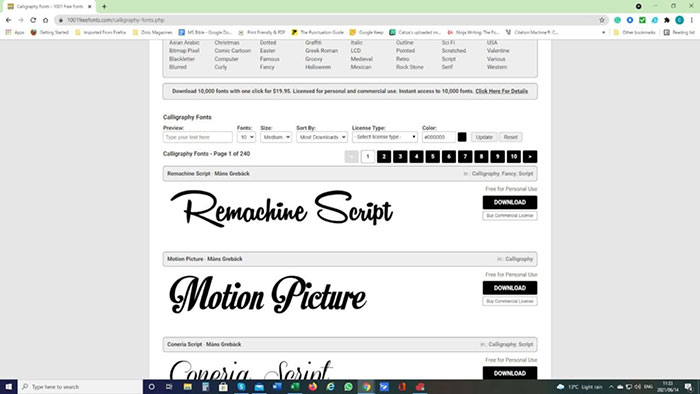
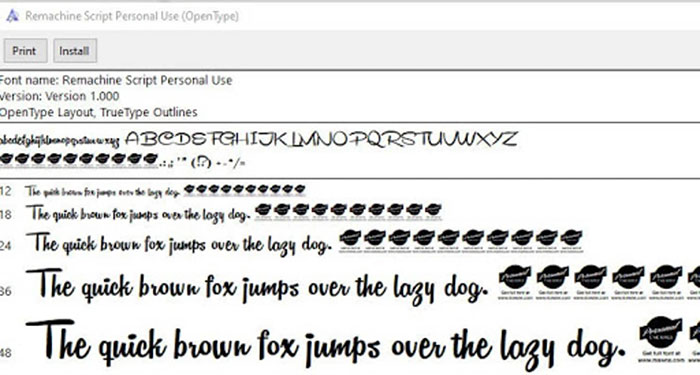
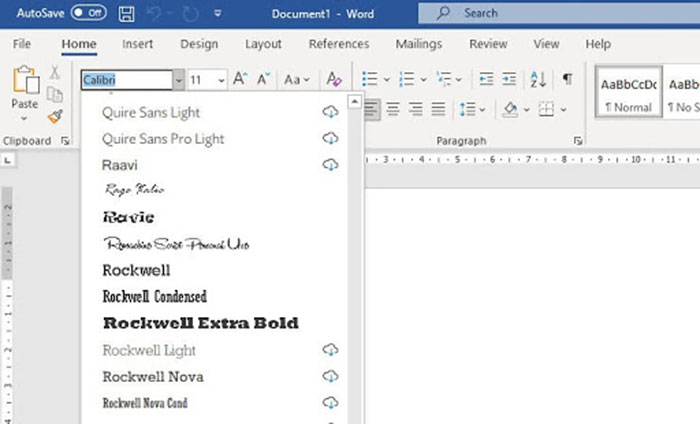
Ngoài ra, việc thêm font vào thư viện font chữ khá dễ dàng nhưng cũng cẩn thận để tránh bị lỗi font. Nhiều font chữ có thể trông đẹp mắt, nhưng không được hỗ trợ tiếng Việt, dẫn đến tình trạng lỗi font. Nếu mọi người phải dành thời gian cố gắng giải mã những gì bạn đã viết thì sẽ gây ra rất nhiều phiền toái.
Việc thêm phông chữ vào thư viện Fonts của Microsoft rất dễ dàng, nhưng hãy chọn lựa cẩn thận. Nhiều phông chữ có thể trông rất đẹp, nhưng văn bản gần như không thể đọc được khi bạn gõ cả một từ bằng chúng. Tình trạng này càng tồi tệ hơn đối với những độc giả khiếm thị hoặc những người đọc trên màn hình điện thoại di động. Nếu mọi người phải mất thời gian để cố gắng giải mã những gì bạn đã viết, họ rất có thể sẽ bỏ cuộc và rời khỏi trang.
Sử dụng phông chữ một cách khéo léo có thể tạo ra sự khác biệt lớn cho các trang web của bạn. Phông chữ có xu hướng gợi lên cảm xúc ở người đọc, và chính cảm xúc này biến phông chữ từ văn bản trên trang của bạn thành một thành phần tích hợp của toàn bộ bố cục.